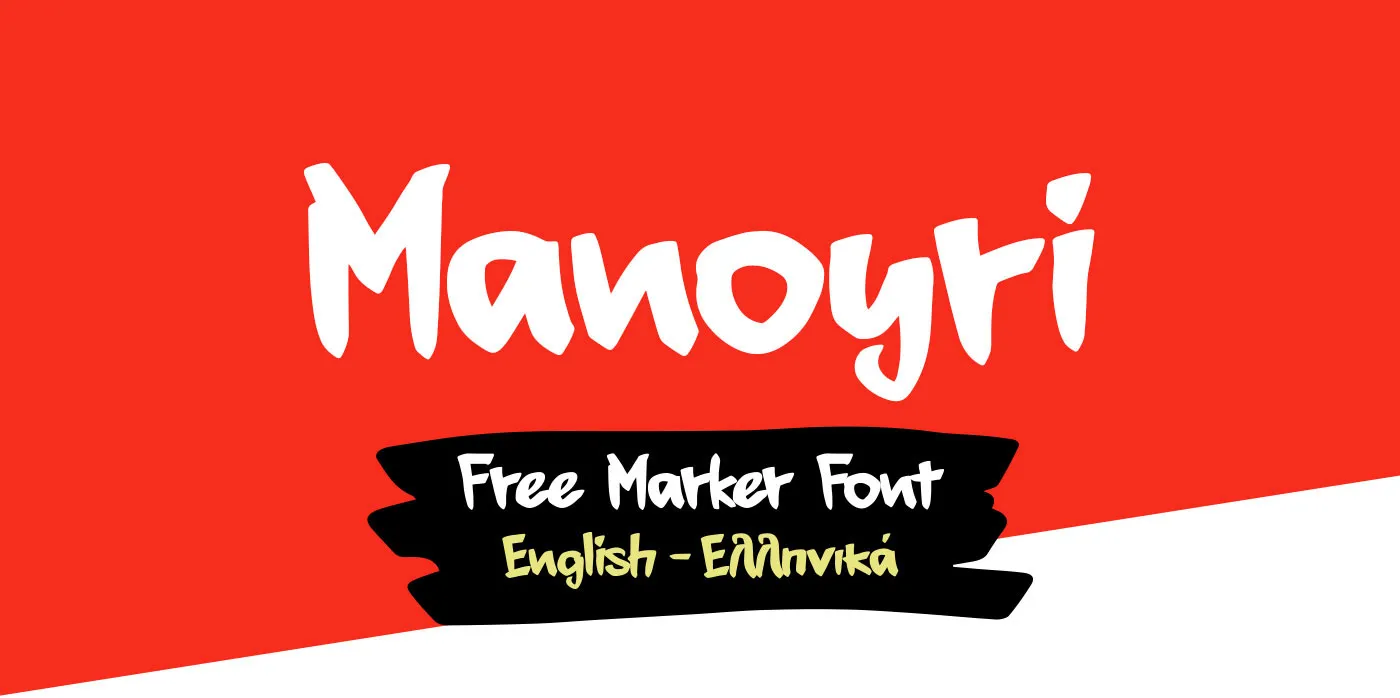
Manoyri Marker Font – Download Grátis
Introduzimos Manoyri Marker Font! Este elegante desenho script foi criado por Stergios Tsiamis e Iordanis Passas, ambos compartilhando-o completamente de graça. É uma fonte de escrita à mão que combina linhas dramáticas e deslizantes com um traço fino de esponja. Este é um elemento decorativo perfeito para objetos pessoais, interiores, cobertores, camisas, cartazes, impressões, casamentos, roupas, embalagens, convites e muitos outros elementos. Além disso, você pode colocar estes frases em suas fotos. Com certeza vai adicionar um toque especial a tudo isso!